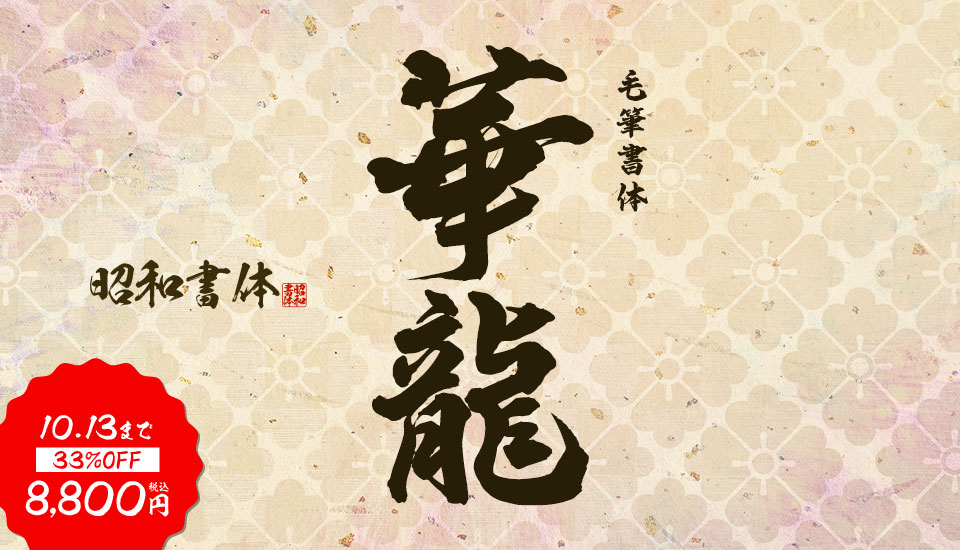
昭和書体 華龍書体 女流書家 西村一華
あらゆる使用目的にマッチできる毛筆書体をめざし、揮毫職人が1文字1文字丁寧に書き上げた本格毛筆書体ブランド『昭和書体』から、女流書家 西村一華が手掛けた第一弾「華龍書体」が登場。
女流書家 西村一華について
「楽しく、仲良く、活気ある教室」を目指して日々の指導に励むかたわら、賞状、棟札、表札、魚拓などの揮毫でも活躍している女流書家。
本作『華龍書体』は、氏が書道教室を開いて25年という節目の年に、それまで辿ってきた道を振り返りながら、感謝の気持ちとともに書き上げたものとのこと。始筆・右払いなどにその特徴が表れた、まさに元気や活力を感じさせる書体です。
華龍 作例1 華龍 作例2